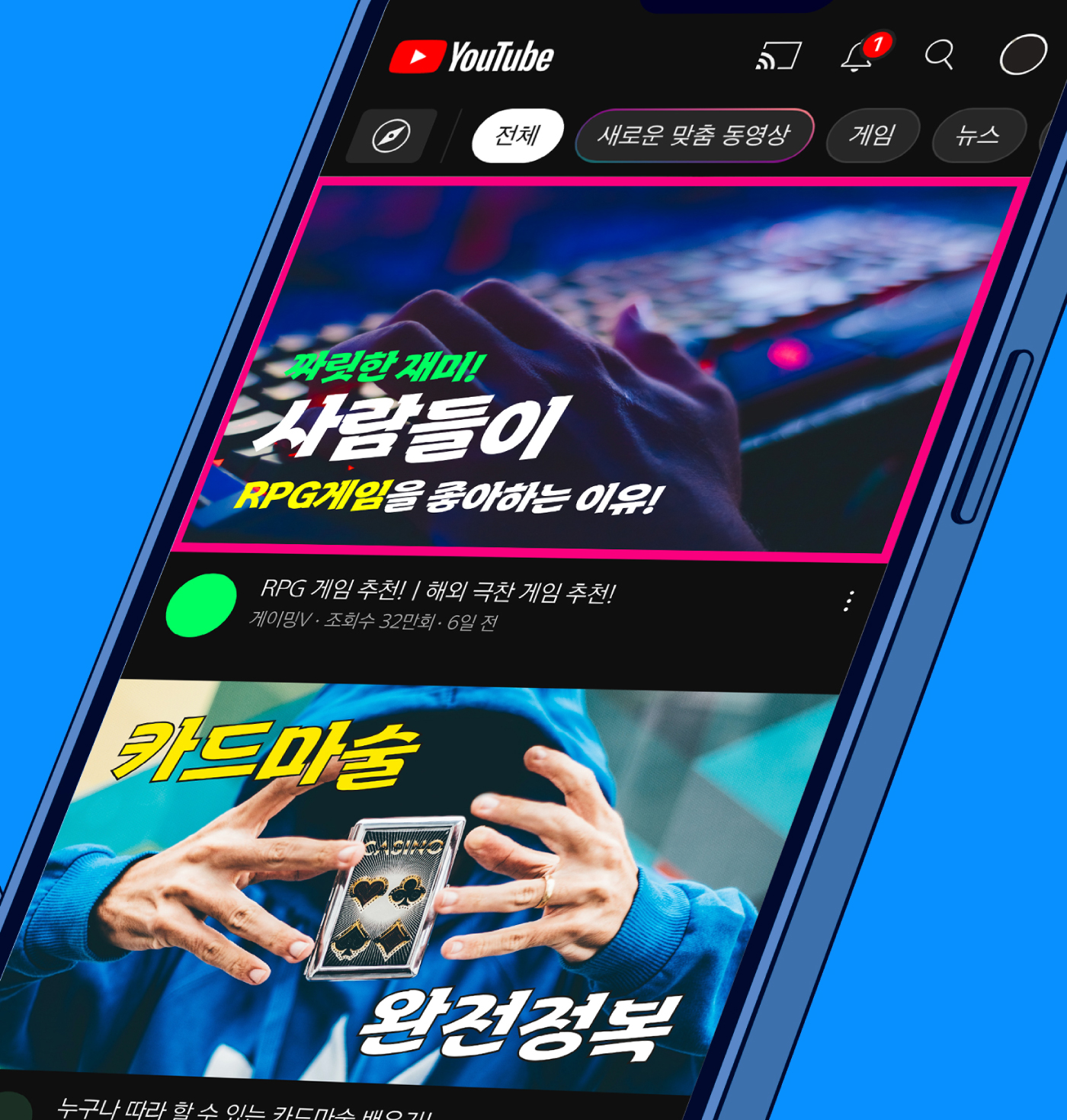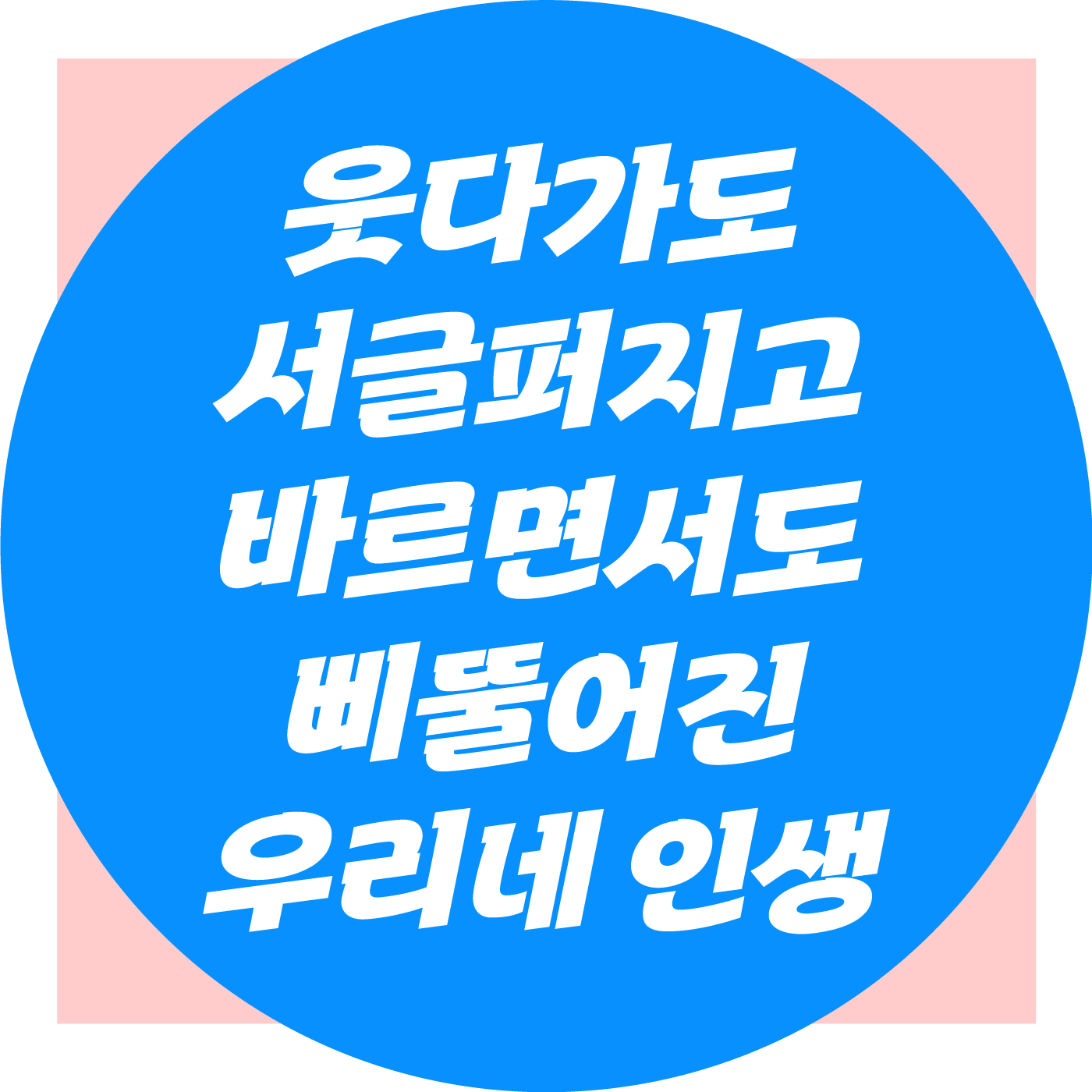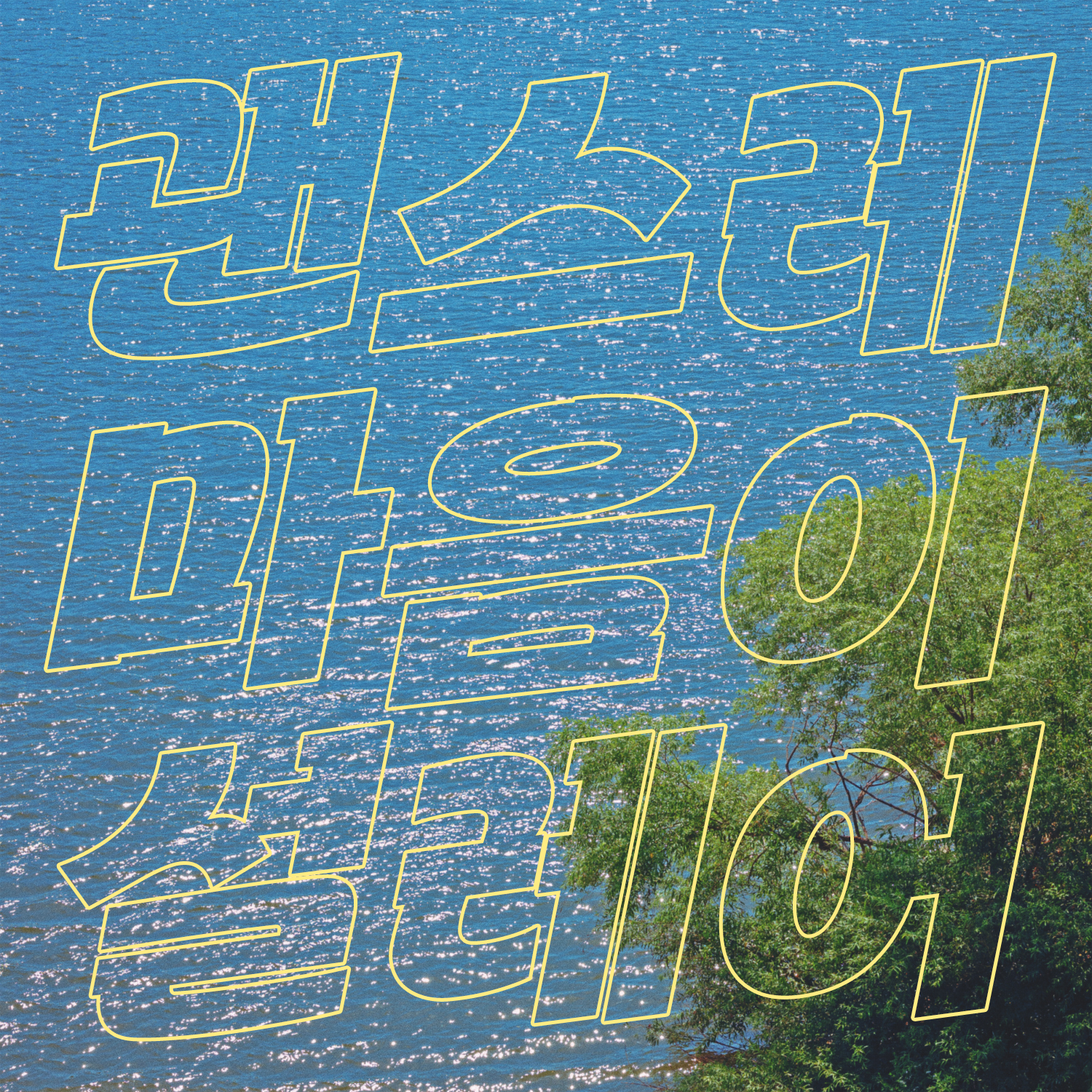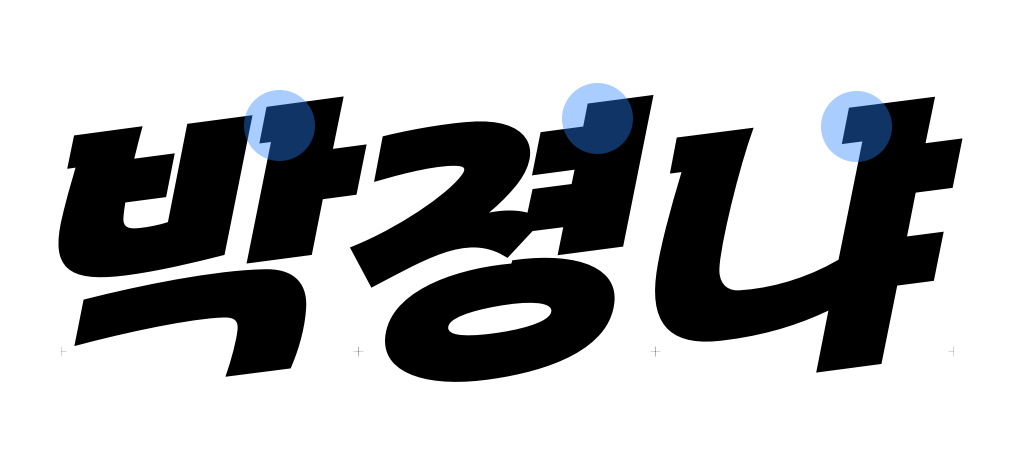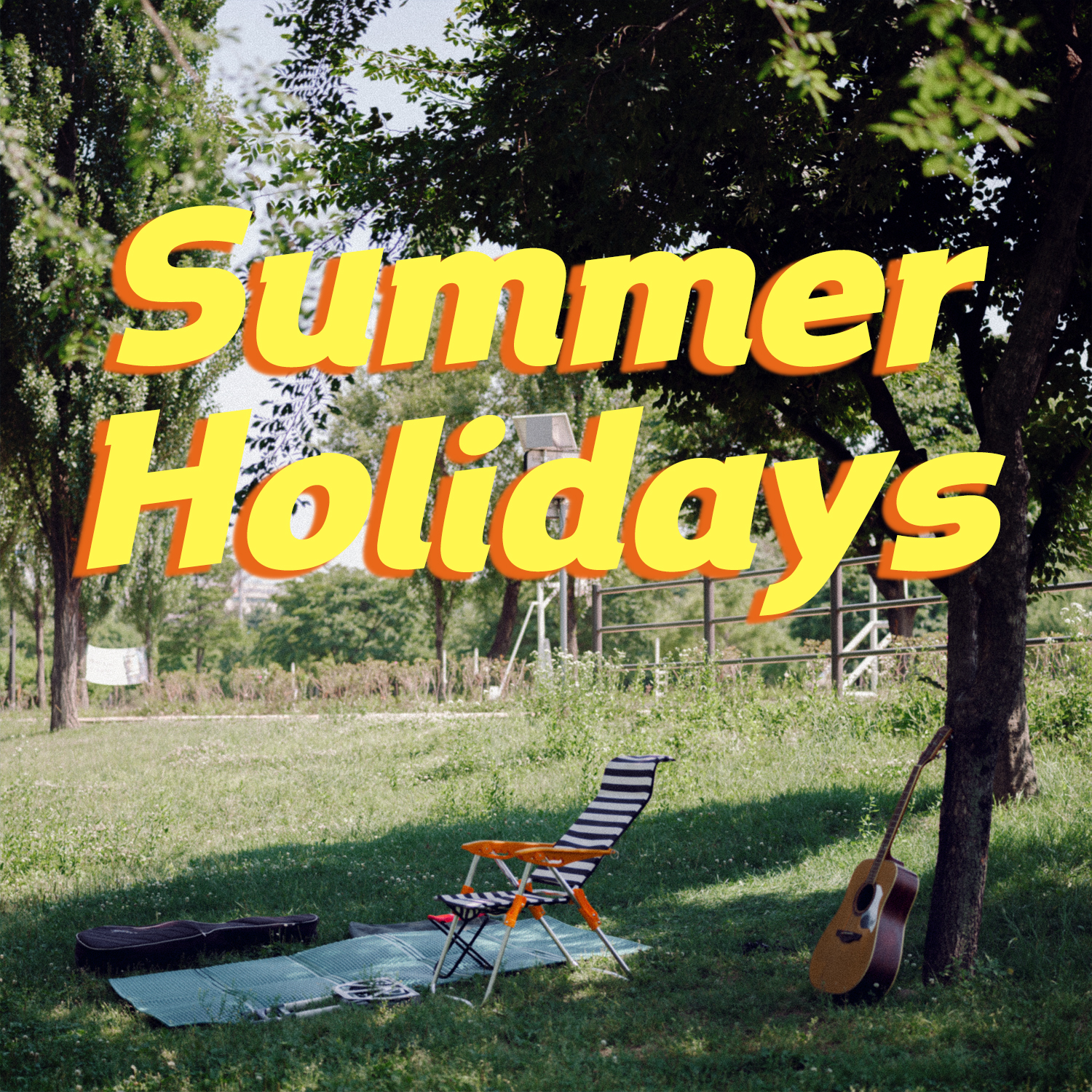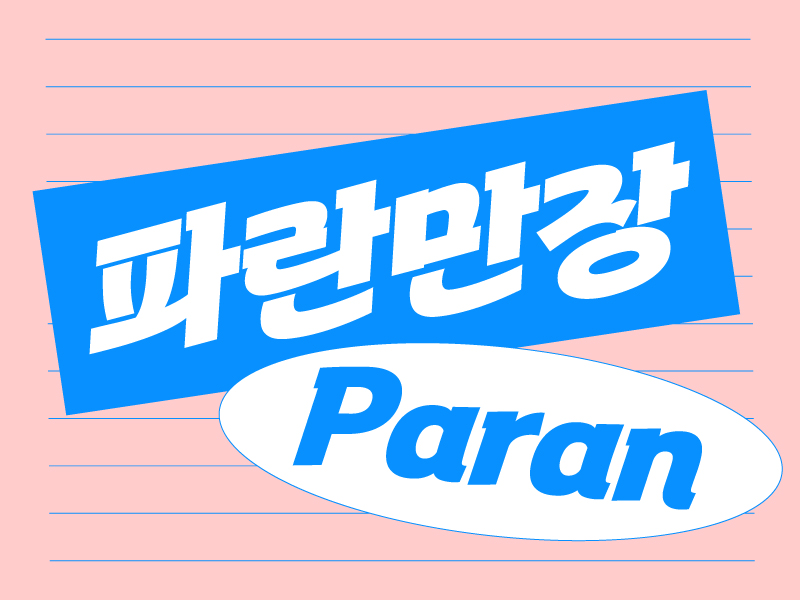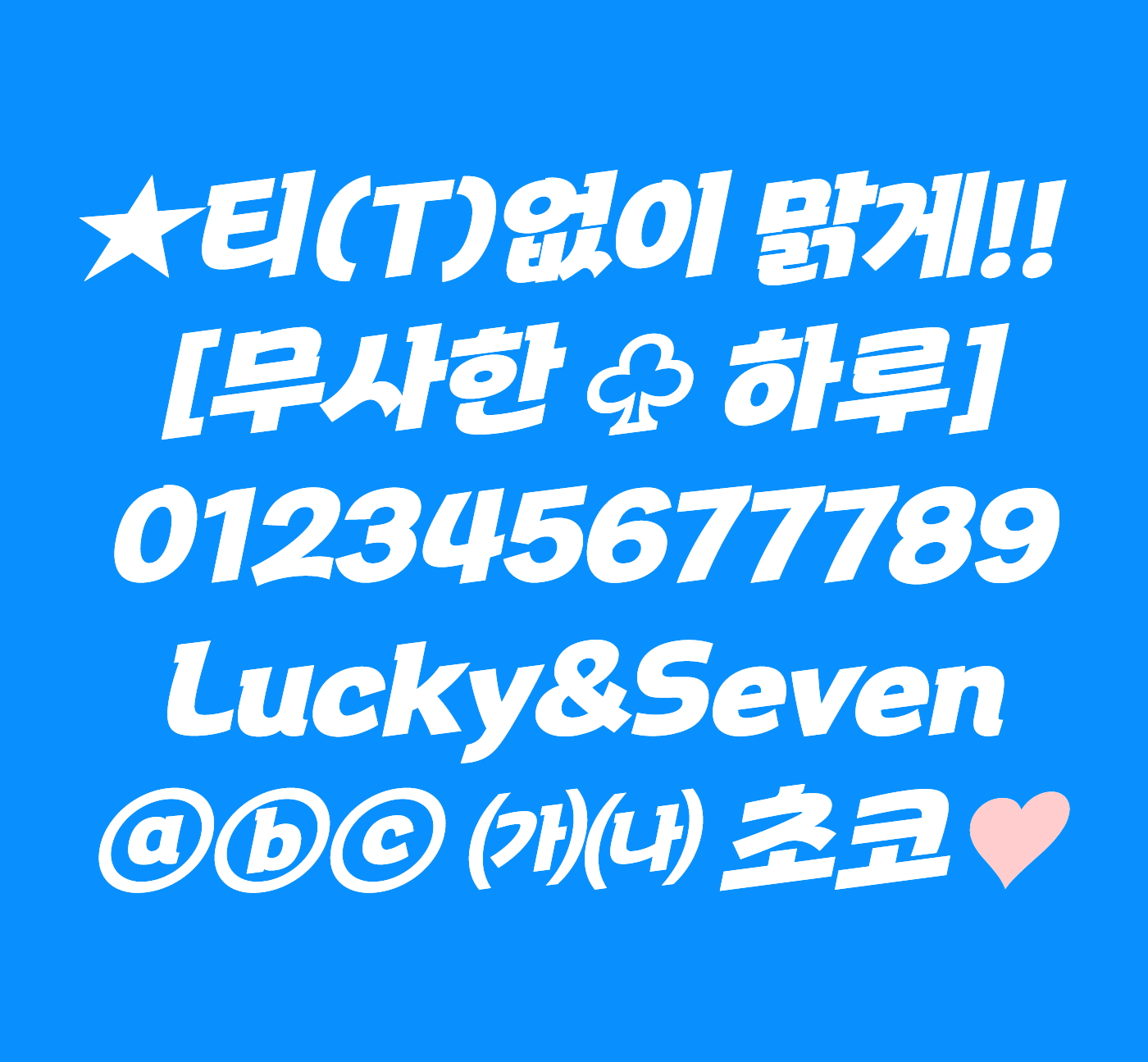
세리프로 캐주얼하게, Rix파란만장
안녕하세요. 이름처럼 파란만장한 날씨가 이어지는, 8월의 신규 폰트 「Rix파란만장」을 소개합니다. Rix파란만장 폰트는 과감한 기울기와 빠른 획순이 역동적이고 캐주얼한 인상이 느껴지는 서체입니다. 이번 폰트를 제작해 주신 박지영 디자이너를 인터뷰를 통해 만나봤습니다 :)
안녕하세요, 박지영 디자이너님. 이번에 새로운 폰트와 함께 인터뷰하게 되었는데 인사 부탁드려요.
안녕하세요. 파란만장으로 돌아온 박지영입니다!
이번 서체 Rix파란만장은 어떤 서체이고 어떻게 제작하게 된 폰트인가요?
레퍼런스를 찾는 과정에서 손맛이 가미된 고딕류의 폰트나 레터링 작업을 자주 볼 수 있었습니다. 딱딱한 고딕과 부드럽고 자유로운 손글씨 획 디자인의 조합이 생각보다 다양했고, 그 조합들이 대체로 무겁지 않은 인상을 하고 있었습니다. 이러한 레퍼런스를 통해 캐주얼하게 쓰일 수 있는 서체를 만들어보고 싶어 기획하게 되었습니다.
‘세리프’가 있는데 캐주얼한 인상을 가진 것이 눈에 띄네요.
이 서체에서 세리프는 속공간에 따라 커지거나 작아지기도 하고 아예 사라지기도 합니다. 필요에 따라 조절할 수 있어 작업할 때 오히려 득이 되었어요. 그리고 디자인 면에서도 가로세로 폭의 두께 차가 별로 없는 슬랩 세리프가 너무 진지한 분위기로 가지 않되, 주목성을 높여준다고 생각했습니다.
사실은 기획을 할 때 산세리프 버전도 함께 기획했었는데, 세리프의 유무에 따라 생각보다 많은 부분이 변화했고, 막상 몇 글자를 제작해 보니 세리프가 있는 디자인이 더 마음에 들었습니다. 그래도 나중에 시간이 있다면 산세리프도 추가로 제작해 사용성을 넓힐 수 있게 되면 좋겠습니다.
제작자 입장에서 파란만장 폰트의 가장 자랑하고픈 부분은?
가로 세로로 기울기가 심한 폰트를 제작하는 게 처음이라 아쉬운 부분들이 있는데, 반대로 생각하면 그 기울기가 강점인 것 같아요. 빠른 획순의 디자인과 만나 더 힘 있고 역동적으로 느껴집니다.
글꼴이 어떻게 쓰였으면 좋겠는지, 추천하는 활용법.
제작하면서 SBS 예능 ‘런닝맨’처럼 급박한 상황이 많은 예능 프로그램에서 포인트 자막용으로 쓰이면 재미있겠다고 생각했어요. 다양한 색깔을 입혀 밝은 분위기로 쓰여도 좋을 것 같아요. 지금까지 읽어주셔서 감사합니다!
필기감이 느껴지는 세리프
Rix파란만장은 두꺼운 웨이트의 1종으로 이루어져 있습니다. 속도감이 느껴지는 기울기와 자유롭고 부드러운 손글씨 획순으로 캐주얼한 인상을 줍니다.
획의 대비가 적은 슬랩 세리프*가 눈에 띄는데요. 두께가 일정한 획이 깔끔한 느낌을 주고, 위의 인터뷰에서 디자이너님의 말씀대로 속공간의 크기, 자소 조합에 따라 세리프가 더 커지기도, 작아지기도 하며 없어지기도 하는 점이 파란만장체의 특징입니다.
슬랩 세리프(Slab Serif)
두껍고 반듯한 조각이라는 뜻의 Slab과 세리프가 합쳐진 말로 획의 두께가 일정한 굵고 각진 세리프
영문이나 숫자, 특수문자 등에도 같은 특징이 적용되어 한글과 자연스럽게 어우러지게 사용할 수 있습니다. 캐주얼하고 트렌디하게 활용하기 좋아요😎
이렇게 활용해 보세요📌
속도감이 느껴지는 서체 스타일이 리얼리티 예능이나 빠른 화제 전환이 필요한 유튜브 등 영상 콘텐츠의 타이틀로 잘 어울려요. 두꺼운 굵기와 적당한 세리프로 무겁지 않게 주목도를 높여줍니다.
이렇게 여름이 느껴지는 콘텐츠와 함께 텍스트 폰트로 활용하기에도 좋은 파란만장 서체! 여러 이미지와 조합을 해보았는데 감성적이고 힙한 이미지와 특히 잘 어울리는 것 같아요.